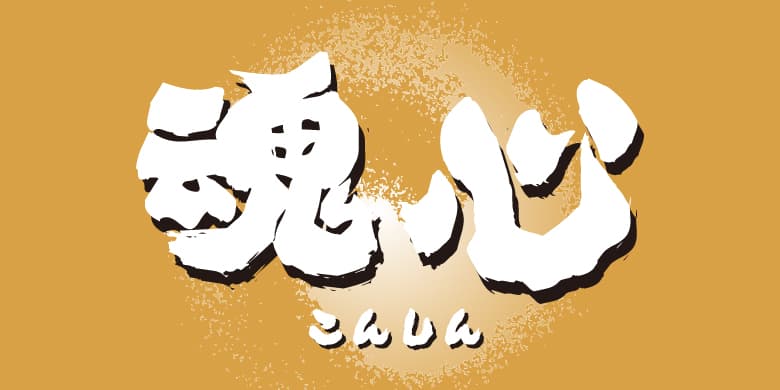
方正白舟魂心体
方正白舟魂心体是一款倾注全身力量书写的字体,由惯用右手的书法家使用左手书写制作的,用笔震颤曲折,仿佛一条蜿蜒的河流,在笔锋处留有点墨,更显深邃悠远。方正白舟魂心体笔画极粗,结构有紧有放、坚实有力,如果在大字号的标题字场合下使用,能让人切实感受到那种充满人情味的力量感。这款字体的原始字符由藤本惠书写创作而成。